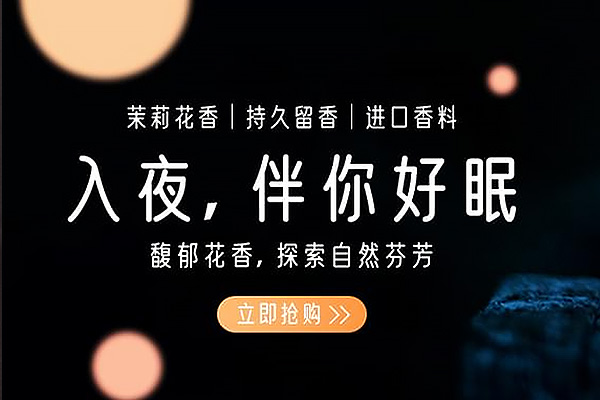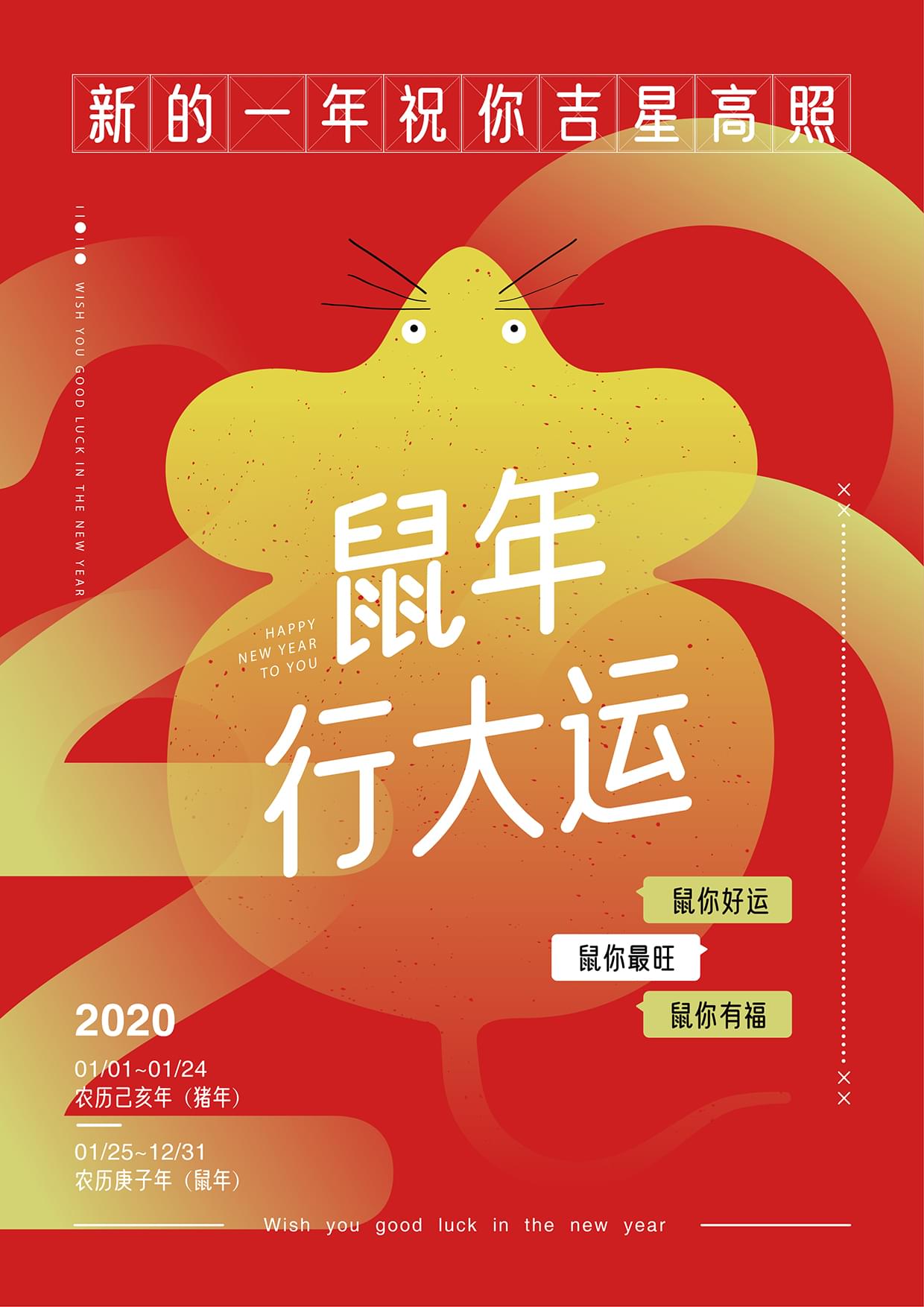
优设好身体
优设好身体是一款具有亲和力和现代感的专业美术标题字体。它以圆体字型为基础,通过瘦高的字面和偏向几何的曲线,为整个字体赋予了独特的亲和力和时尚感。在相同的面积内,由于字面较窄,因此可以容纳更多的信息。这款字体非常适合应用于各类品牌宣传广告和产品包装设计中,能够突出亲和力和时尚感。
优设好身体字体的命名和风格在去年10月就已经确定下来。我们希望设计师们使用这款字体后能够减少改稿次数,少熬夜,保持身体健康。在当前疫情形势下,我们更是希望每个人都能像这款字体名字一样拥有一个好身体!
优设好身体效果预览
优设好身体字体效果预览